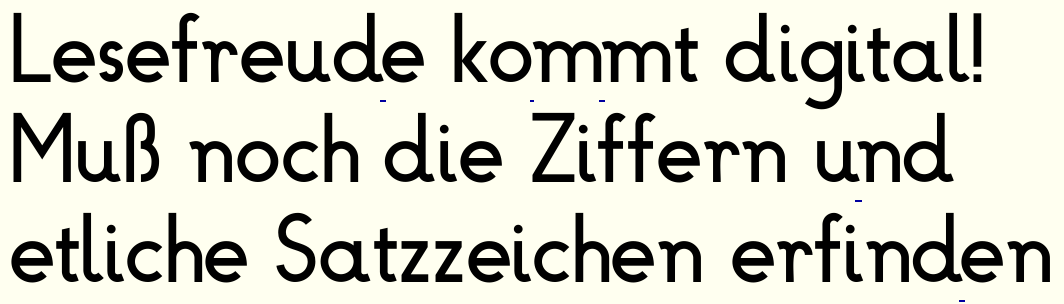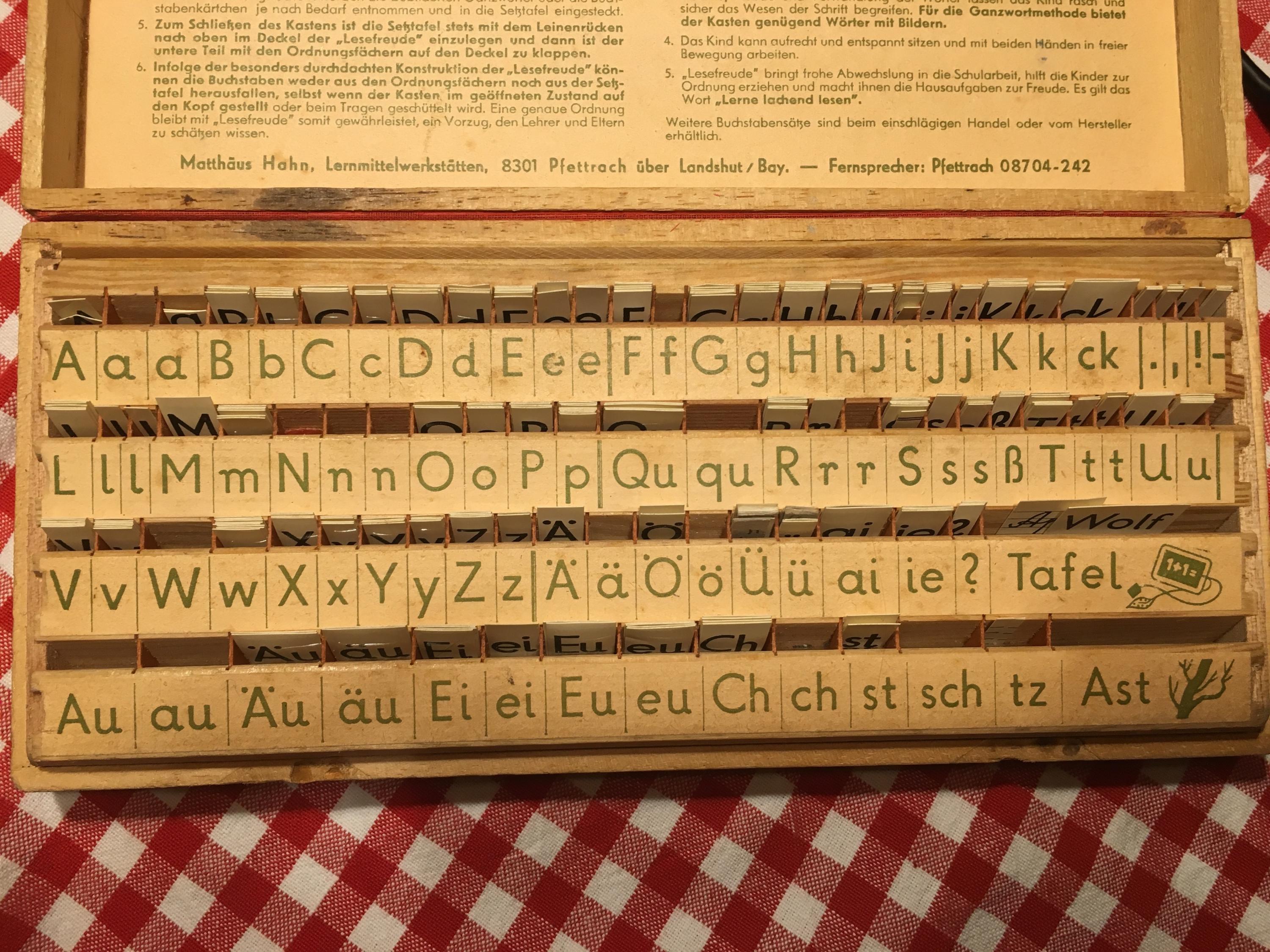
Suche Schrift Hahn Oldenbourg Lesefreude von 1971
ich bin im Internet auf der Suche nach der Schriftart dieses Schul Setzkastens von 1971.
1972 bereits war die Schrift eine andere.
Vielleicht könnt ihr mir hier helfen und wisst zufällig welche Schrift das sein könnte.
Dann werde ich die so nicht als Systemschrift für den Rechner finden und nutzen können.
Futura mit Schwänzchen an a, l, m, n, r, t und u.
Find’ ich jetzt gar nicht dumm. Für meine in Futura gesetzten Kinderbücher wäre das sicher eine bessere Alternative gewesen. Gib’s nichts in der Richtung? Ansonsten: @catfonts? 8-)
ja, habe mir das Bild schon gespeichert und etwas entzerrt. Zumal, die hat auch das "große große I", Vielleicht sollte es ja, folgt es auf andere Grußbuchstaben über OpenType das gerade "kleine große I" ersetzt werden?
Na ja, Ziffern, sowie §$%&*+# ist ja wohl nicht dabei gewesen. Also habe ich den ganzen Kram eben nach Gefühl gezeichnet. Ich hoffe das passt einigermaßen - wenn nicht, bitte meckern!
Hier der eiligst zusammen genagelte Font :-)
Sehr schön :-)
Meine beiden Cent:
– bei % und ‰ finde ich die Kreise zu groß
– © und ® finde ich zu dick und zu schlecht erkennbar
Ich wusste jetzt nicht, wie du "für meine Illustration auf meiner Website" meinst – um eine Illustration daraus zu erstellen, wären die Bilder ja brauchbar.
Zum s: Ja, das ist verdammt schmal, aber ich wollte ja diese Buchstabier-Kärtchen Schrift 1:1 nachbauen, und da bringt das die Konstruktion der Buchstaben so mit sich.
Mein Auge ist natürlich nicht das beste, was Fontdesign angeht, und das Photo ist auch perspektivisch nicht gänzlich optimal, aber mir deucht das s fast so breit wie das r.
Dieses Missverhältnis kommt daher, das alle Rundungen in den Buchstaben aus Kreisen konstruiert sind, hierdurch ist das s zwangsweise nur halbe x-Höhe breit, während b, d, e, o eben den Raum der vollen X-Höhe einnehmen.
Wobei man nun vielleicht auch nicht jede Schlampigkeit wiederholen muss. Es gibt ja auch nur ein Beispiel eines ß. Die Buchstaben, die mehrfach vorhanden sind, unterscheiden sich ja teilweise deutlich.
ich hatte die Buchstaben auch nicht durchgepaust, sondern nach grobem Ausmessen der Versalhöhe und x-Höhe dazu dann nach den in der Schrift erkannten Konstruktionsprinzipien völlif frei, nur durch Vergleich mit dem Bild auf den 2. Monitor in Coreldraw gezeichnet. Hier nur die Mittellinien mit einer Strichbreite von 80 Punkten bei einer Versalhöhe von 720 Punkten. Beim ß war das auch nicht so einfach, die Konstruktion von meinem Vorgänger zu erkennen.